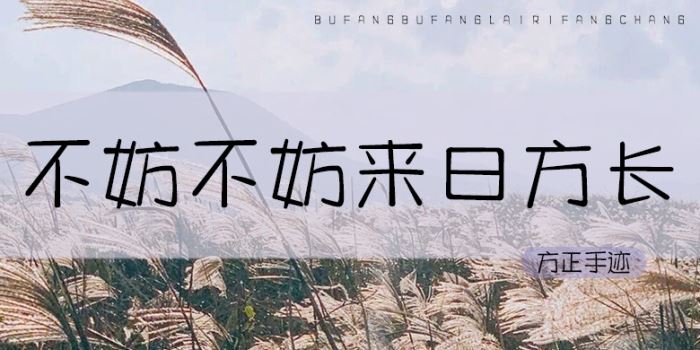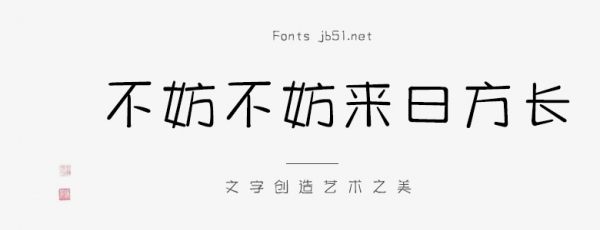
方正手跡-不妨不妨來日方長由方正字庫蘇新詩設計師出品的藝術字體,字體重心偏中,字面相對較大,筆畫簡潔,適合應用于藝術設計、平面宣傳設計、網(wǎng)頁設計,書法等領域。
該字重心偏中,字面相對較大,筆畫簡潔,因而有良好的閱讀體驗。適用于現(xiàn)代詩歌、短文的排版,以及屏顯、影視綜藝,及文化、商業(yè)類品牌的廣告語設計。